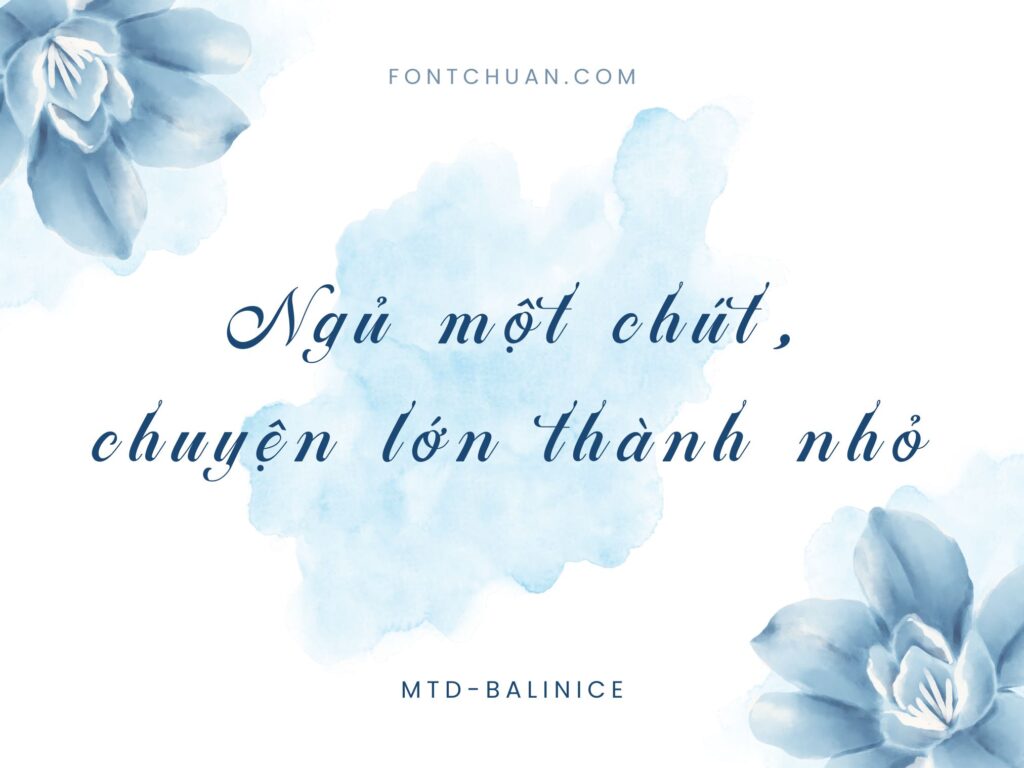
Font MTD Balinice Việt Hóa
Balinice là một font chữ thanh lịch được thiết kế bởi Typelinestudio, mang phong cách hiện đại và mềm mại. Font này nổi bật với các đường nét bay bổng, giúp tạo ra sự tinh tế và sang trọng trong các thiết kế đồ họa. Nhằm hỗ trợ cộng đồng thiết kế Việt Nam, Mộc Hạ đã Việt hóa font Balinice, giúp font này tương thích hoàn toàn với tiếng Việt cùng hơn 200 ngôn ngữ khác. Phiên bản Balinice Việt hóa đã được thành viên Font Chuẩn sưu tầm và đăng tải, nhằm mang đến sự lựa chọn phong phú hơn cho các nhà thiết kế.
Về đặc điểm thiết kế, Balinice sở hữu các ký tự uốn lượn mềm mại, kết hợp với độ tương phản nhẹ để tạo cảm giác tinh tế và sang trọng. Font này được thiết kế đặc biệt để phù hợp với các dự án typography nghệ thuật, thiệp cưới, logo thương hiệu cao cấp và bìa sách. Ngoài ra, Balinice cũng thích hợp cho các ngành nghề như quảng cáo, ẩm thực và giáo dục, mang đến phong cách thanh lịch và chuyên nghiệp.